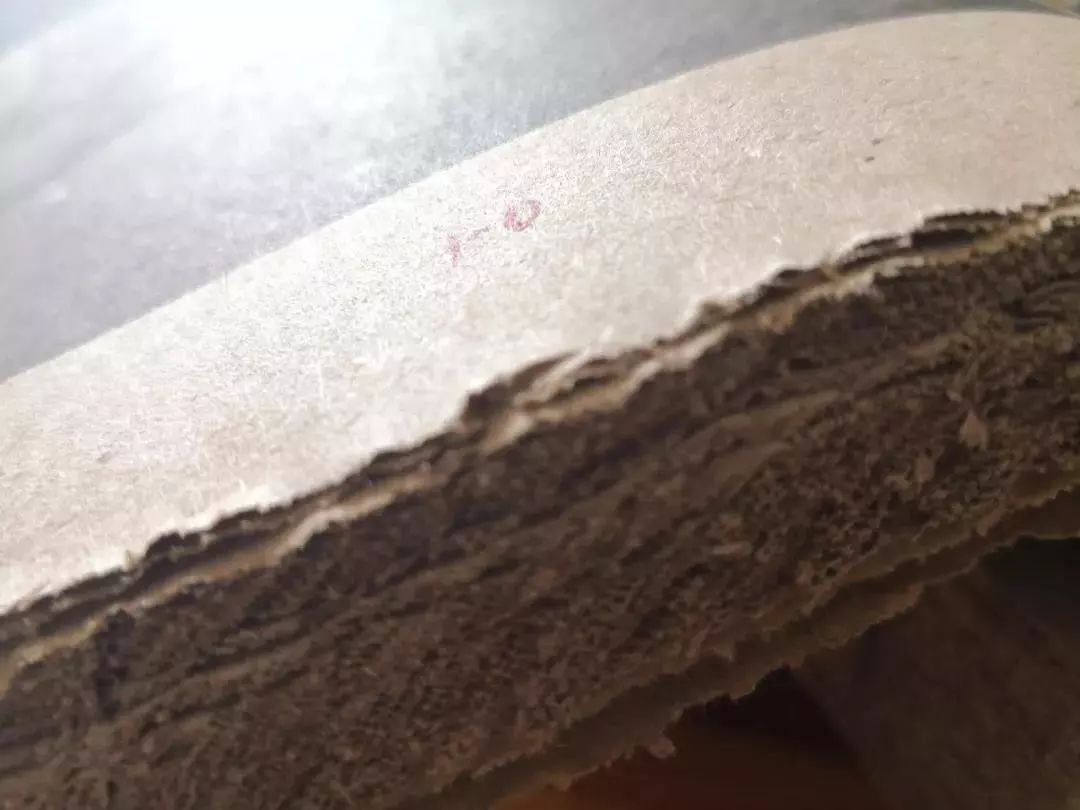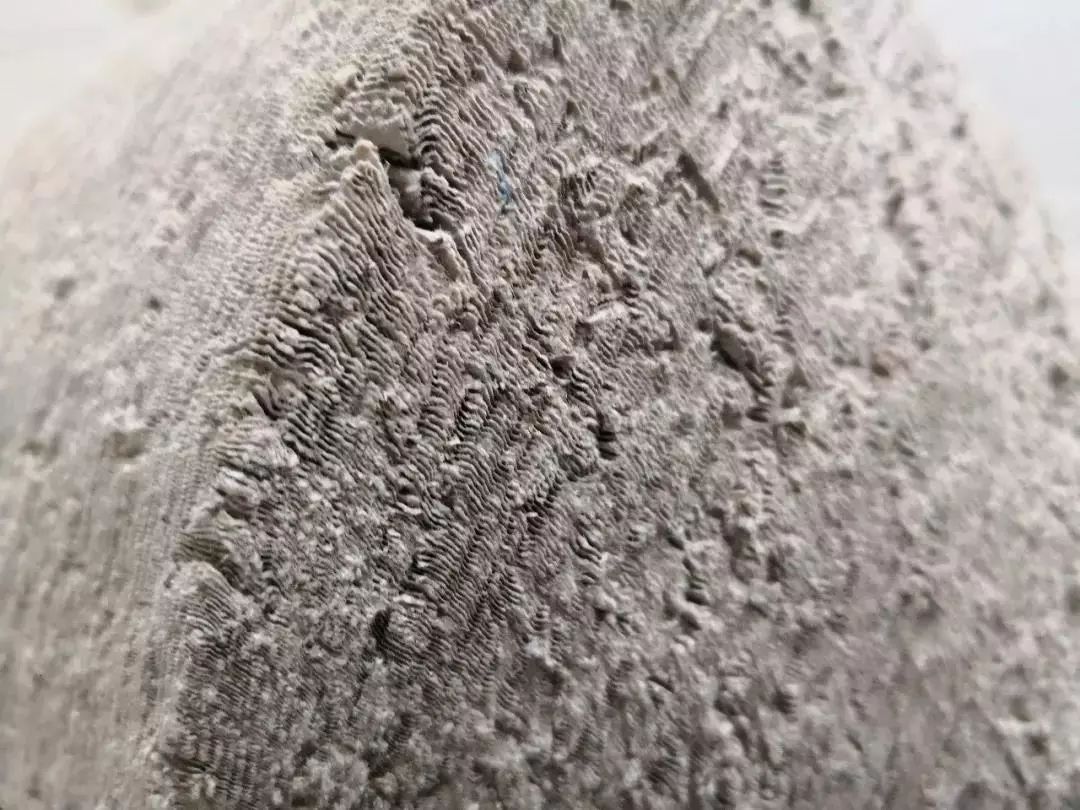
美翻!这20本“世界最美的书”都出自中国设计师
《江苏老行当百业写真》获2019“世界最美的书”荣誉奖
三月,14本“世界最美的书(Schonste Bucher aus aller Welt)”获奖书籍于德国莱比锡揭晓。
“世界最美的书”是由德国图书艺术基金会主办的评选活动,距今已有近百年历史,代表了当今世界书籍艺术设计的最高荣誉。评委会由来自德国、英国、瑞士、荷兰、罗马尼亚等国的著名书籍艺术家、专家组成。
每年一届的“世界最美的书”共评选包括“金字母”奖一名,金奖一名,银奖两名,铜奖五名,荣誉奖五名,共计14种获奖图书。
从左至右,从上至下,依次为“金字母”奖(1名),金奖(1名),银奖(2名),铜奖(5名),荣誉奖(5名)。
由上海市新闻出版局、“最美的书”评委会选送的《江苏老行当百业写真》从34个国家和地区的600多件参评作品中脱颖而出,获“世界最美的书”荣誉奖。这也是本届“世界最美的书”唯一获奖的中国书籍。
荣誉奖
《江苏老行当百业写真》
龚为 摄影
潘文龙 撰文
江苏凤凰教育出版社
2018年6月
《江苏老行当百业写真》由江苏凤凰教育出版社出版、周晨设计,龚为摄影,潘文龙撰文。设计师同时也是本书的选题策划者,书稿由长期关注老行当的摄影家和作家合作完成。老行当,是对社会上正在消失的各行各业的总称,虽渐行渐远,却承载着民间的独特智慧和一代人共同的回忆。本书依据行当特点及旧时传统,将江苏的老行当分为八类,通过严谨的设计语言,塑造民间气质,是一部致敬匠心之作。
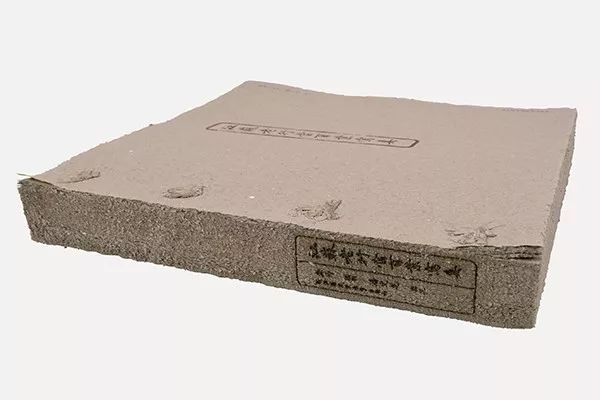
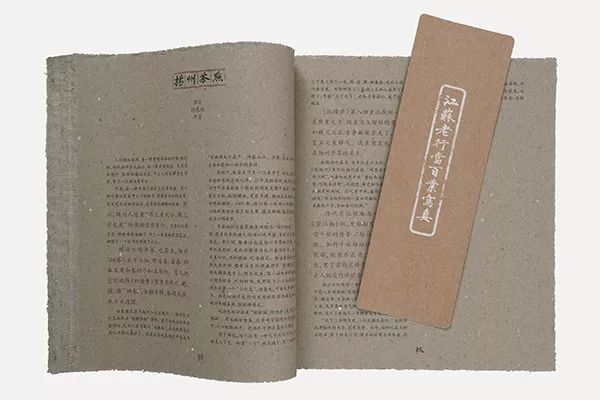
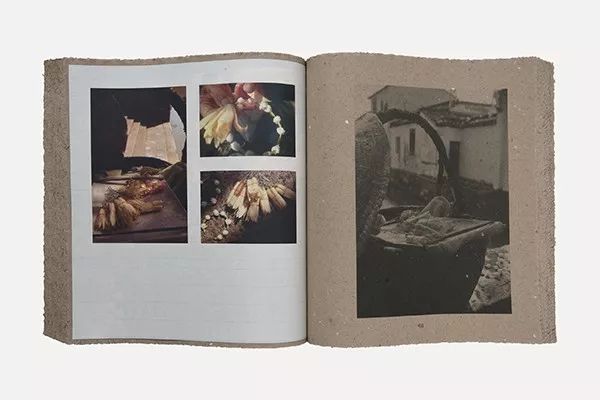
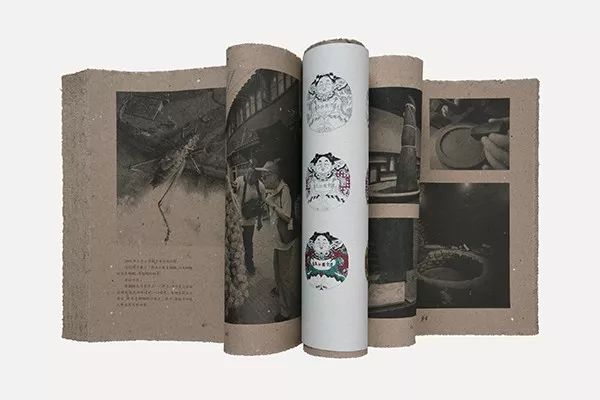
作者:周晨
周晨,江苏凤凰教育出版社编审、艺术出版中心主任,中国美术家协会会员,苏州大学艺术学院硕士生导师,中国版协装帧艺委会常务委员。书籍设计作品入选8次“中国最美的书”,“第八届全国书籍设计艺术展”社科类最佳作品,“第九届全国书籍设计艺术展”社科类金奖,第四届中国出版政府奖,“2016年67届、2017年68届美国印制大奖”最高荣誉班尼奖金奖,2016年“香港第28届印制大奖”冠军奖,2017年香港第29届印制大奖最佳书籍奖 、匠心大奖、及豪华精装书奖,2017年“世界最美的书”荣誉奖。2014年参加雅昌艺术中心“新造书运动——书籍设计十人展”。特邀担任2015年度“中国最美的书”评委。
/ “最美的书”评委会评语 /
设计处处显示真情,用老店铺包点心的粗陋纸张并打毛边,表现逐渐消失的民间老行当百业,有朦胧之美。采取古老而民间的装订方式,页码设置奇特。内文的文字与大图片使用不同材质来表现,丰富了视觉语言。黑白图片印在粗陋纸张上,产生古老斑驳的意向,仿佛显示了新百业皆源自老行当。
- 荣誉奖 -
《冷冰川墨刻》
书籍设计:周晨
作者:冷冰川
出版:海豚出版社
评委点评
图书封面有刀刻的痕迹,与文本主题高度契合。整体设计的气质比较稳重大方。书籍内黑色部分运用得当,黑白辉映传递出优雅的气质。
/ 2016年 /
- 金奖 -
《订单——方圆故事》
书籍设计:李瑾
作者:吕重华
出版:广西美术出版社
评委点评
封面采用包装纸,书名仿照订单,选材和设计都很新颖。以出版社往来信件作为开头,每一页的签名都附上不同的肖像,趣味十足且富有个性。设计打破常规,在前言和目录之间插入图片,书口呈动画图像翻阅形态,激发读者去探寻和发现。
- 铜奖 -
《学而不厌》
书籍设计:曲闵民、蔣茜
作者:周学
出版:江苏凤凰美术出版社
评委点评
本书使用传统的宣纸来印刷中国画与书法,缀满成像富有质感。部分画页左右上下翻折,赋予阅读以动感,与主题相辅相成。封面用绘画装裱形式制作,工艺手段与内容吻合,裸背装订方式便于翻阅,柔软程度如同品读古籍。文本排列随阅读游动,在规则中寻求着文字群的变化,或虚或实、是有序与无序的对立统一。东方韵味在设计中贯通整体,使得书籍的文人气息和传统审美意识浓郁。
/ 2014年 /
- 铜奖 -
《刘小东在和田&新疆新观察》
书籍设计:小马哥×橙子
作者:侯瀚如、欧宁(主编)
出版:中信出版社
评委点评
本书以一种笔记本的形式记载艺术家的创作经历……富有现场感。精心选择不同的纸张和印刷手段,准确表现内容结构的丰富性。编辑设计概念明晰,使繁复的体例结构严谨、层次清晰,布局合理,尤其对每一个细节的处理都不轻易放弃……章隔页用油画布丝网印独具匠心,封面用材及周边打毛,有着强烈的触感,体现出随意放在包中的笔记本不断使用的时间概念……
- 荣誉奖 -
《2010-2012:中国最美的书》
书籍设计:刘晓翔工作室·刘晓翔
作者:上海市新闻出版局 “中国最美的书”评委会
出版:上海人民美术出版社
评委点评
封面以装帧布材与纸材直接裱被,具实用感的韧性,耐翻并间距视觉与触觉的材质变化,情趣。全书整体设计简约大器,具新颖的现代感;装帧方式全书为曲折页,具庄重的仪式感,翻阅时与读者产生互动。全书图版全部由设计师统一规划拍摄,体现了严谨的视觉呈现,图片处理调性雅静、视觉丰满柔和。图版与内容版面统一,折页装订契合准确;纸张运用讲究,双卖弄涂布;细节考虑到位,虽用四方网格设计的语言形式,却创造出中国式的空灵。充满中国式的空灵,恰好地体现了“中国最美的书”的内涵,高雅、高品位的呈现。
/ 2012年 /
- 银奖 -
《剪纸的故事》
书籍设计:敬人设计工作室·吕旻、杨婧
作者:赵希岗
出版:人民美术出版社
评委点评
该书设计多彩、有趣、活泼、友善,与主题结合紧密。选用的纸质十分考究,具有很高的艺术性。
- 荣誉奖 -
《文爱艺诗集》
书籍设计:刘晓翔、高文
作者:文爱艺
出版:作家出版社
评委点评
整体设计简洁而有个性。字体、颜色之间动静对比强烈,富有视觉冲击力。护封下部文字从封面延续至封底,体现了流动的美。
/ 2011年 /
- 荣誉奖 -
《漫游:建筑体验与文学想象》
设计:小马哥×橙子
作者:欧宁(编)
评委点评
封面设计采用中国古代现状形式,简洁明快,同时附有时尚感。纸质柔软,层次感鲜明,颜色选用自然色,排版新颖。建筑照片与草图交相辉映,富有层次。阅读本书仿佛在经历一次探险。
/ 2010年 /
- 荣誉奖 -
《诗经》
书籍设计:刘晓翔
作者:向熹(译注)
出版:高等教育出版社
评委点评
这是古今对照的形式编排的305首诗,除了原诗以外,加了经译、注释、韵读等内容。版面的合理规划及安排下体现出现代感。用色简洁,字体及字号的选择考虑了区分不同内容的功能性,予古籍以清爽现代的风尚。运用不同纸材区隔风、雅、颂,极大地扩展了诗的想象空间。
/ 2009年 /
- 荣誉奖 -
《中国记忆——五千年文明瑰宝》
书籍设计:敬人设计工作室·吕敬人、吕珉
编者:首都博物馆(编)
出版:文物出版社
评委点评
这是一本特展图录,整体装帧的概念元素取材自中国传统文化中虚实空间对立的概念。由外至内,从书匣的外封到图录的封面,在视觉质感上层层体现出阳刚与阴柔的变幻。尤其是采用柔软纸材加上类似中式装订的形式,这种中国富豪在细节上的运用,产生了有别于传统图录的特征与质感,也增强了阅读的层次感。
/ 2004年 /